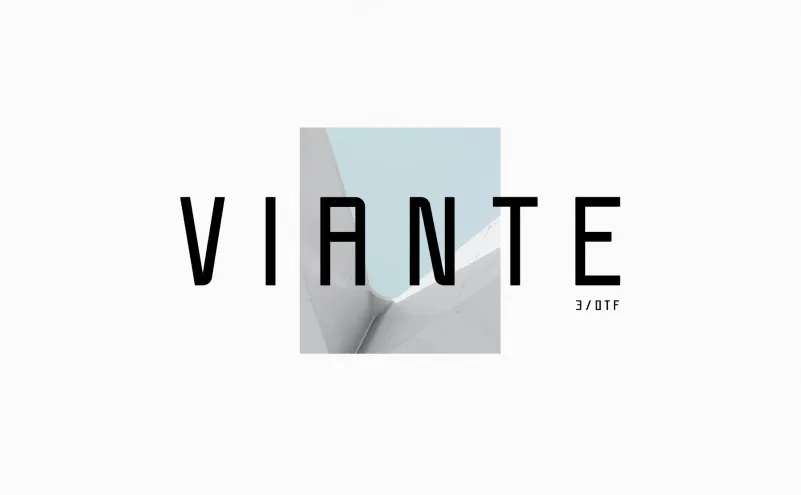
A fonte Viante é uma opção moderna para designers que buscam um estilo elegante e sofisticado. Desenvolvida pela Createby Sunjun, esta tipografia atende a uma ampla variedade de projetos, como assinaturas, embalagens, logos, capas de livros ou revistas, sites, materiais de viagem e até mesmo roupas de grife. Seu estilo elegante e moderno faz dela um recurso ideal para estilos de exibição que valorizam sofisticação e criatividade. Viante é uma fonte perfeita para designers em busca de elementos que se destacuem no design gráfico, dando ao seu trabalho uma aparência única e profissional.